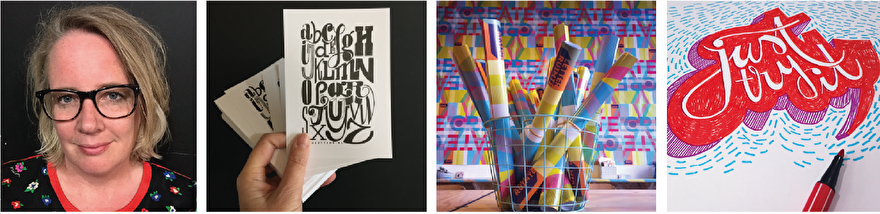
Wie is handletters.nl?
Mijn naam is Mirjam de Boer. Ik bèn handletters.nl. Omdat ik nu eenmaal graag met mijn handen letters teken, maak en letterbeelden creëer. Handletters dus!
In 1999 wandelde ik de kunstacademie (ArtEZ) uit als afgestudeerd Grafisch ontwerpen. Vol dromen en een wereld die open lag. Twee ontwerpbureaus en vier jaar later was mijn conclusie: de hele dag achter een computer is niets voor mij. Ik zit liever met mijn handen in de tape, lijm of verf dan de hele dag op een muis klikken.
Stond ik dan. Wat een geweldige conclusie!
Elf jaar later -ben ik een goedlopend bedrijf in vilten kinderkameraccessoires verder- weet ik één ding zeker: ik wil weer terug naar mijn vak. Ik wil weer zijn waar ik ooit voor studeerde: grafisch ontwerper. Ik besef dat er een énorme lichting ontwerpers na mij is afgestudeerd, en dat er ook heel veel ontwerpers zijn die via een andere weg in dit vak zijn gerold.
Maar wat moet dat moet. Dit is wat ik wil én kan!
De drang om te creëeren met mijn handen, letters te tekenen, te spelen met vorm en kleur. Of ik nu letters schilder, ze uit papier snij of teken met fineliners of gewoon ouderwets schets met potlood. Zolang ik letterbeelden mag maken ben ik waar ik wil zijn.
Door de jaren heen kwam ik er steeds meer achter dat ik een freestyler ben. Dat ik direct kan werken in een korte tijd. Ik draai mijn hand er niet voor om, om in een stressvolle situatie grote borden te letteren. Zoals 15 juryrapporten of conclusies uit werkgroepen die binnen 2 uur gepresenteerd moeten worden op een podium. Geen probleem. Maar ook projecten waar meer proces is zit kan ik aan. Het maken van letterbeelden die gebruikt worden als illustraties of het maken van boekomslagen en posters. Allemaal opdrachten waarin het even anders mag dan de huisstijl. Waarin ik mijn out-of-the-box ideeën rijkelijk kan laten vloeien. En ook met mijn ideeën help ik soms creatieve afdelingen die er niet helemaal uitkomen.
Zet die ideeënfabriek in mijn hoofd maar aan!
Om de creativiteit weer aan te zwengelen, mee te helpen eens out-of-the-box te denken, te experimenteren en gewoon te doen (wat ik freestylen noem) geef ik soms workshops waarin dit centraal staat. Durf en doen.